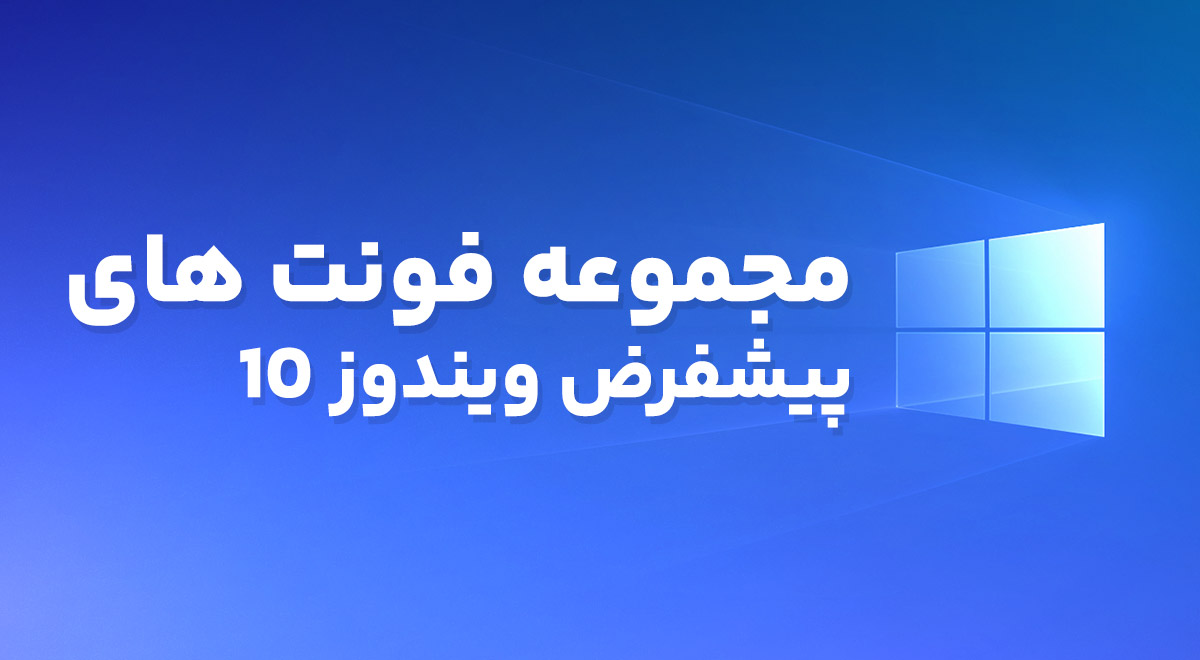
مجموعه فونت های پیشفرض ویندوز 10
فونت های پیشفرض ویندوز 10
فونت چیست؟ فونت به مجموعه ای از حروف، اعداد، نشانه ها و سمبل های طراحی شده با یک سبک و شکل خاص گفته می شود. فونت ها در زبان های مختلف و با استفاده از سیستم های نمایش مختلف مانند کاغذ، صفحه نمایش، پروژکتور و غیره قابل استفاده هستند. فونت ها بر اساس خصوصیات مختلف مانند نام، خانواده، دسته بندی، ضخامت، ارتفاع، عرض، زاویه، فاصله، ترازبندی و غیره دسته بندی می شوند.
فونت پیشفرض ویندوز 10 و نحوه تغییر آن
فونت پیشفرض ویندوز 10 به فونت اصلی و استاندارد این سیستم عامل گفته می شود که در بخش های مختلف محیط کاربری، منو ها، نوار ابزار، فایل اکسپلورر، برنامه ها و غیره به کار می رود. فونت پیشفرض ویندوز 10 Segoe UI نام دارد که توسط شرکت Microsoft طراحی شده است. این فونت با هدف بهبود خوانایی، سادگی، زیبایی و هماهنگی با سبک طراحی Fluent Design System انتخاب شده است.
لیست فونت های پیشفرض ویندوز 10
ویندوز 10 به طور پیشفرض شامل بیش از 100 فونت مختلف است که برای زبان ها و کاربرد های متنوع طراحی شده اند. برخی از این فونت ها جزء خانواده Segoe UI هستند که برای محیط کاربری ویندوز 10 به کار می روند. برخی دیگر جزء خانواده Arial هستند که برای نمایش متن در برنامه ها و وب سایت ها استفاده می شوند. برخی نیز جزء خانواده Courier New هستند که برای نمایش کدهای برنامه نویسی مناسب هستند. لیست کامل فونت های پیشفرض ویندوز 10 را می توانید در این لینک مشاهده کنید.
مزایا و معایب فونت های پیشفرض ویندوز 10
فونت های پیشفرض ویندوز 10 دارای مزایا و معایب خاص خود هستند. برخی از مزایای آن ها عبارتند از:
سازگاری با سبک طراحی Fluent Design System که بر روی تمام اجزای ویندوز 10 اعمال شده است.
خوانایی بالا در اندازه ها و رزولوشن های مختلف صفحه نمایش.
پشتیبانی از زبان ها و حروف نگارش های مختلف با استفاده از فونت های Unicode.
زیبایی و سادگی در طراحی حروف و سمبل ها.
برخی از معایب آن ها عبارتند از:
عدم امکان تغییر فونت پیشفرض به صورت ساده و رسمی در تنظیمات ویندوز 10.
عدم تطابق با سلیقه و نیاز برخی از کاربران که ممکن است فونت دیگری را ترجیح دهند.
عدم دسترسی به فونت های جذاب و خلاقانه که در بازار موجود هستند.